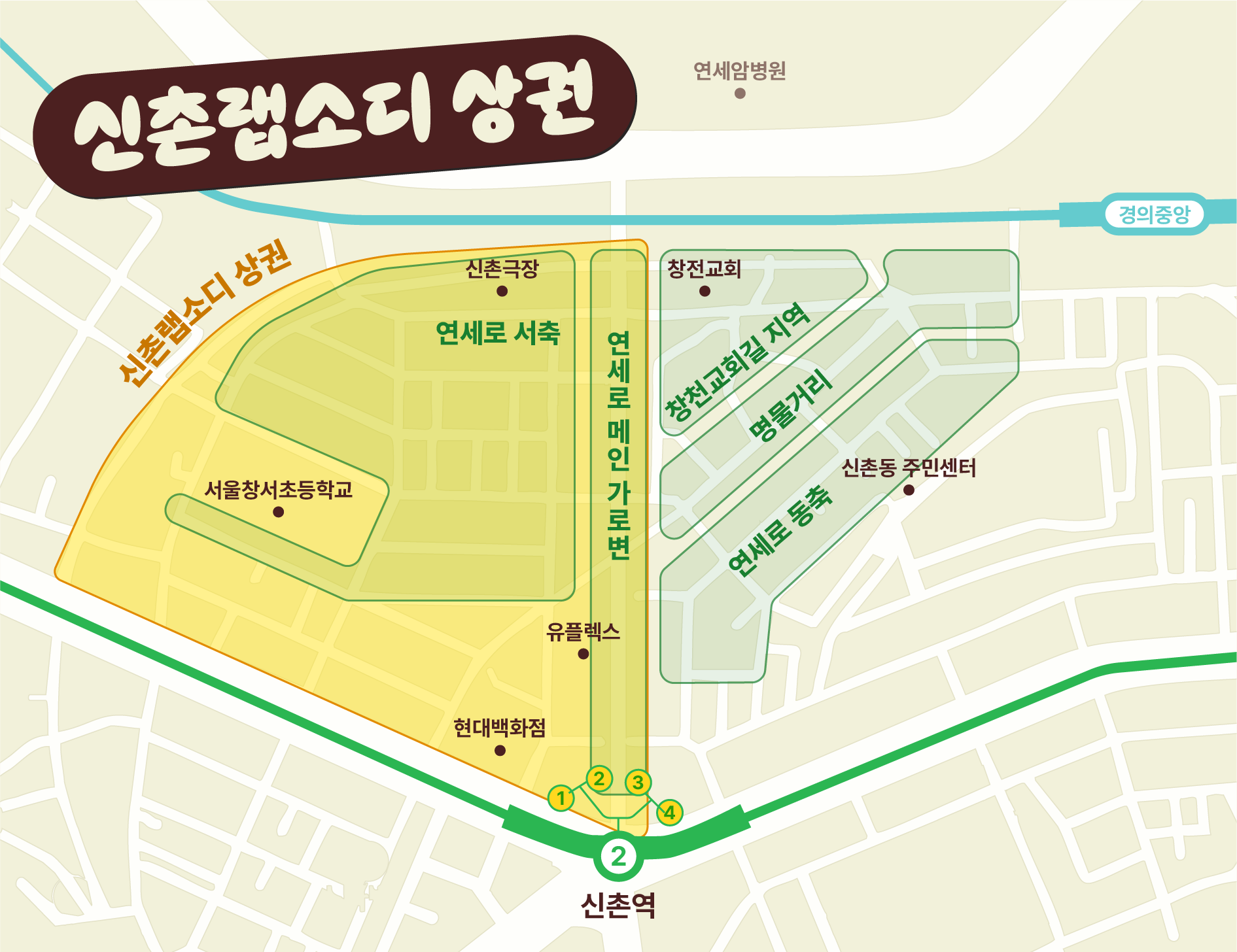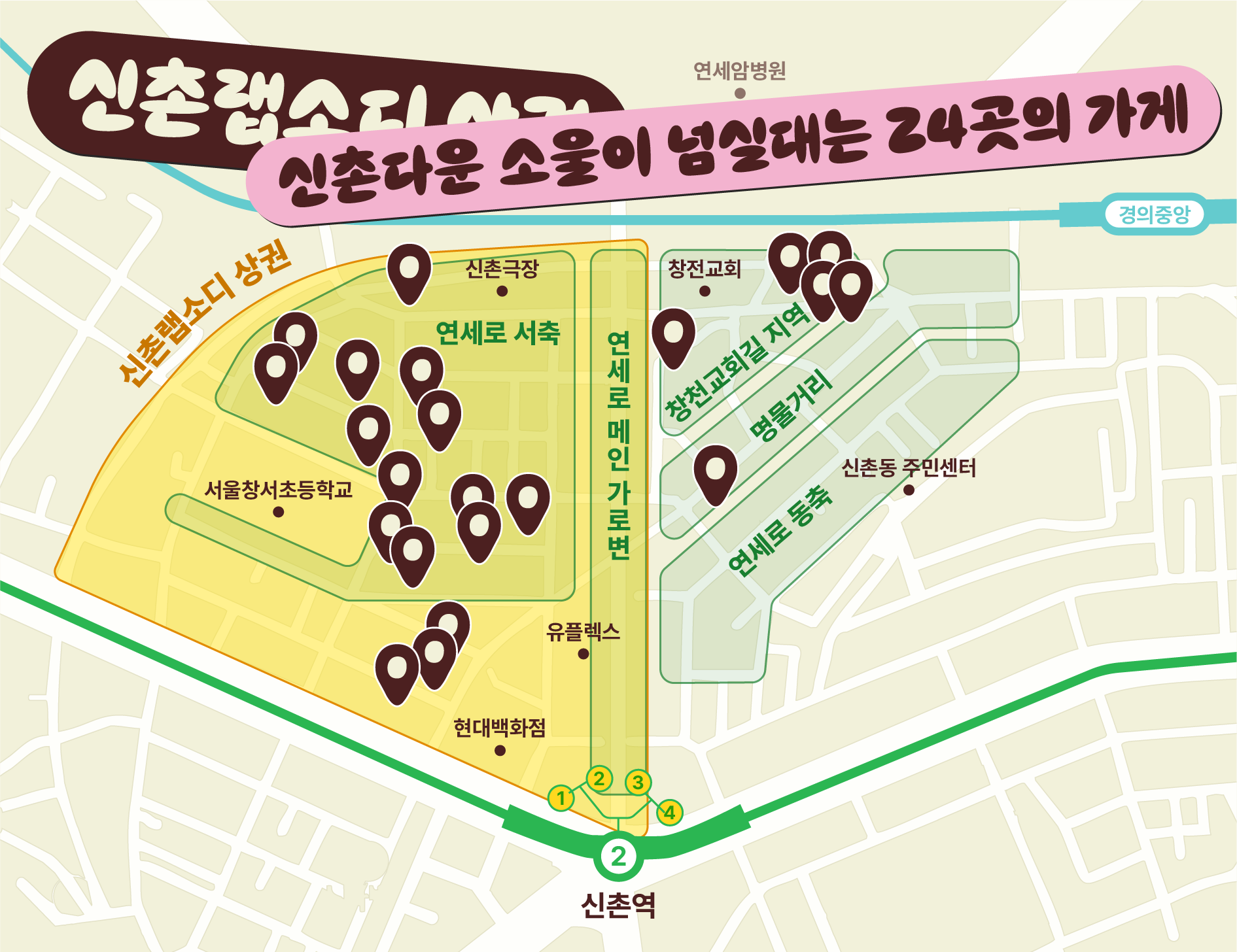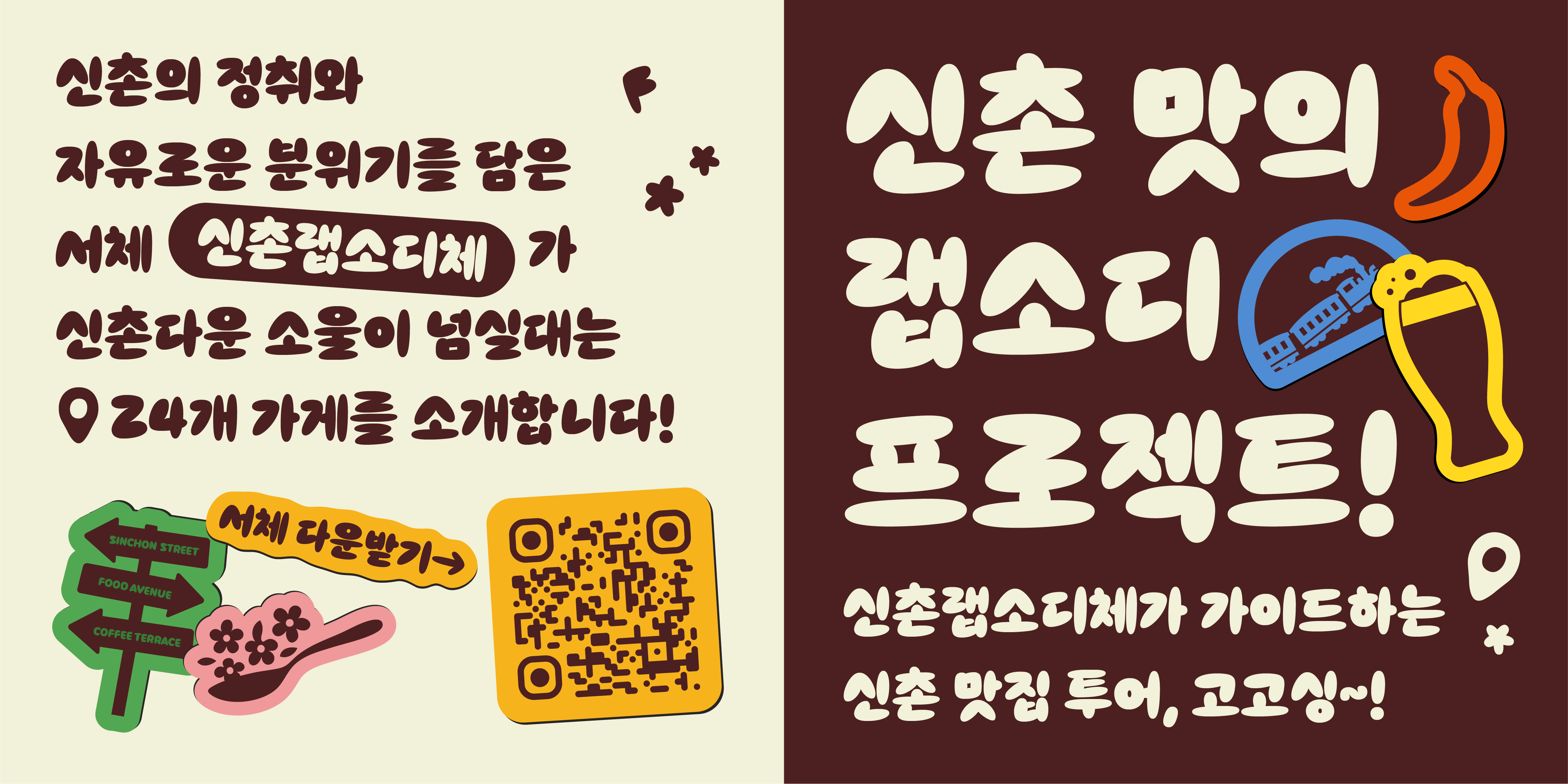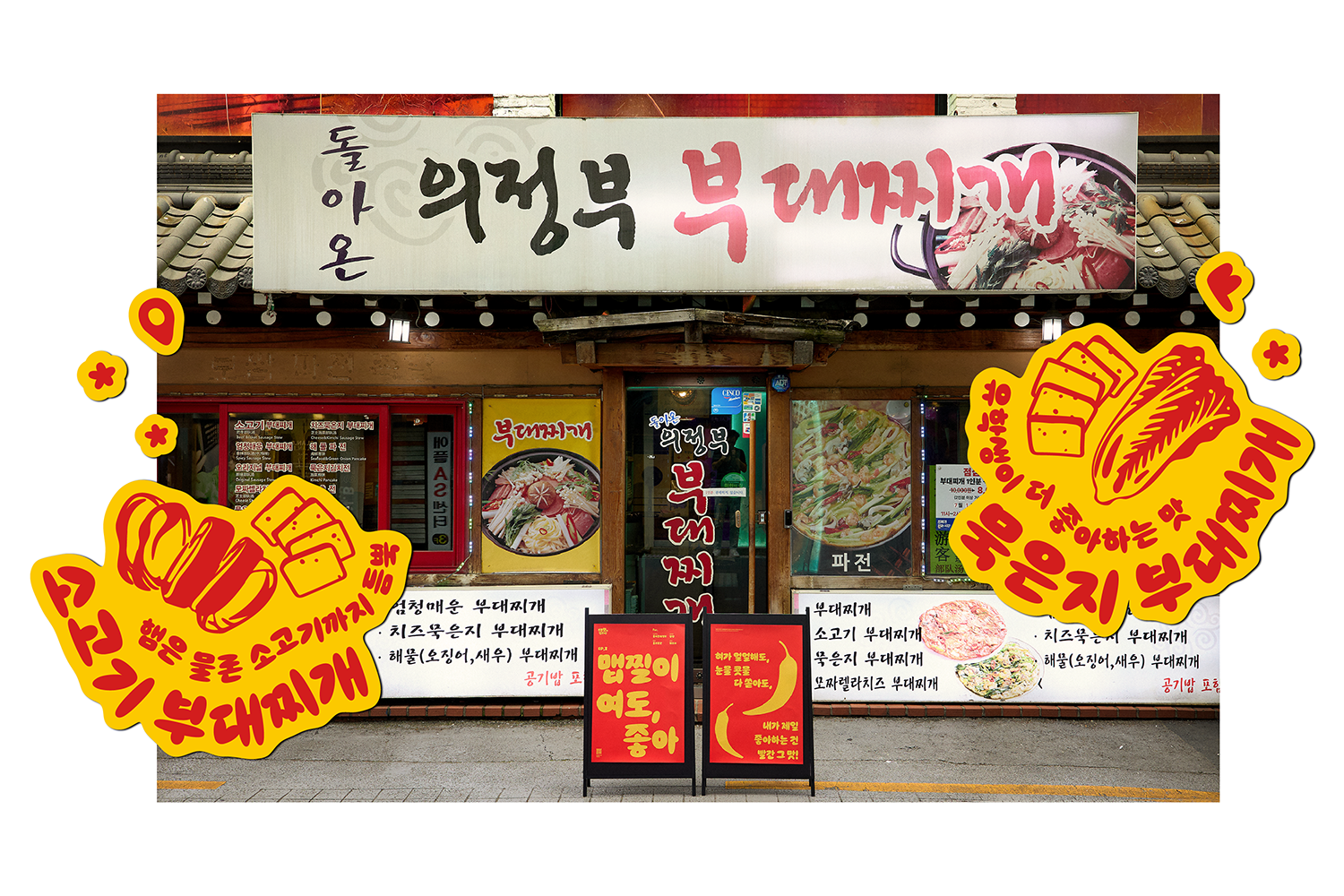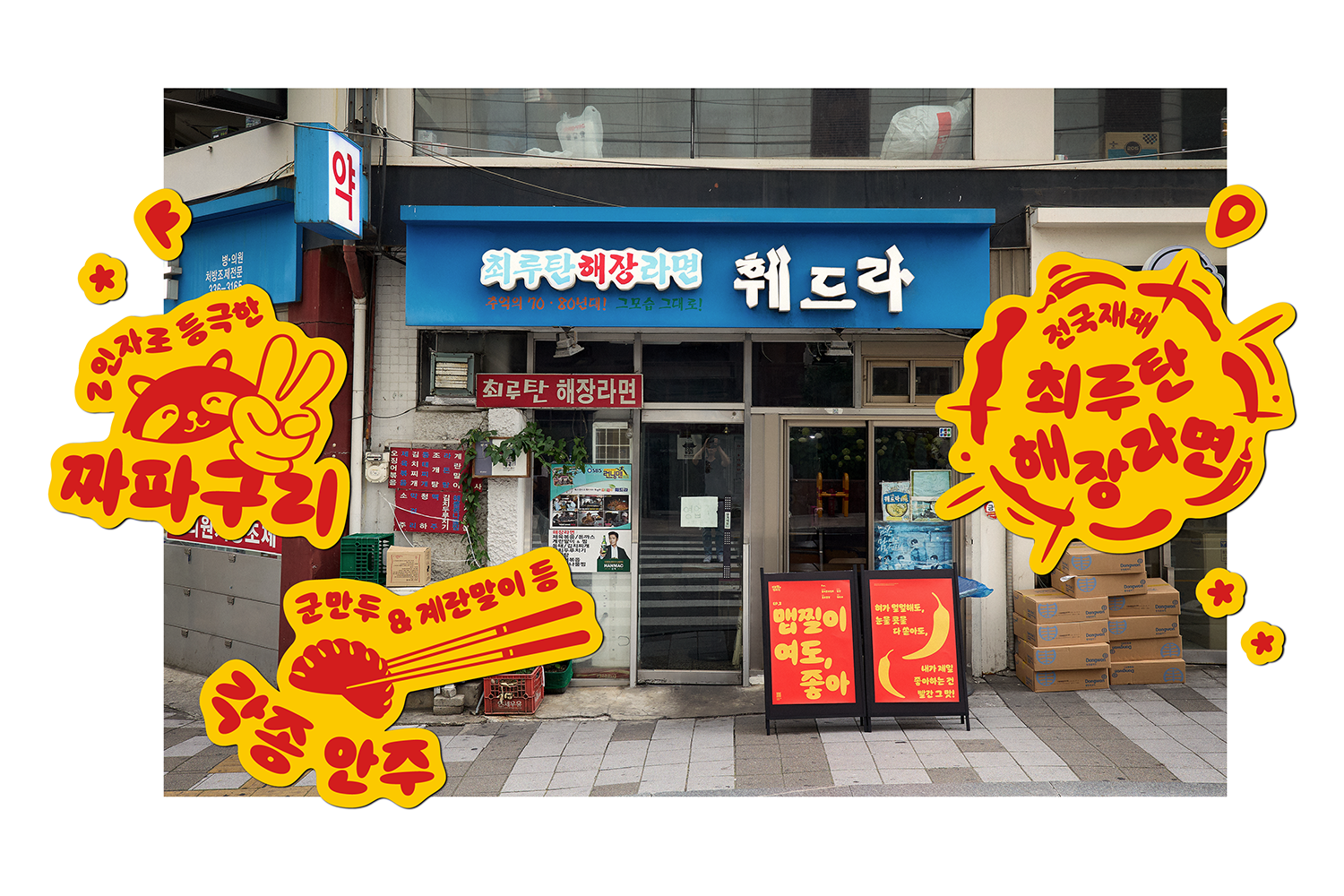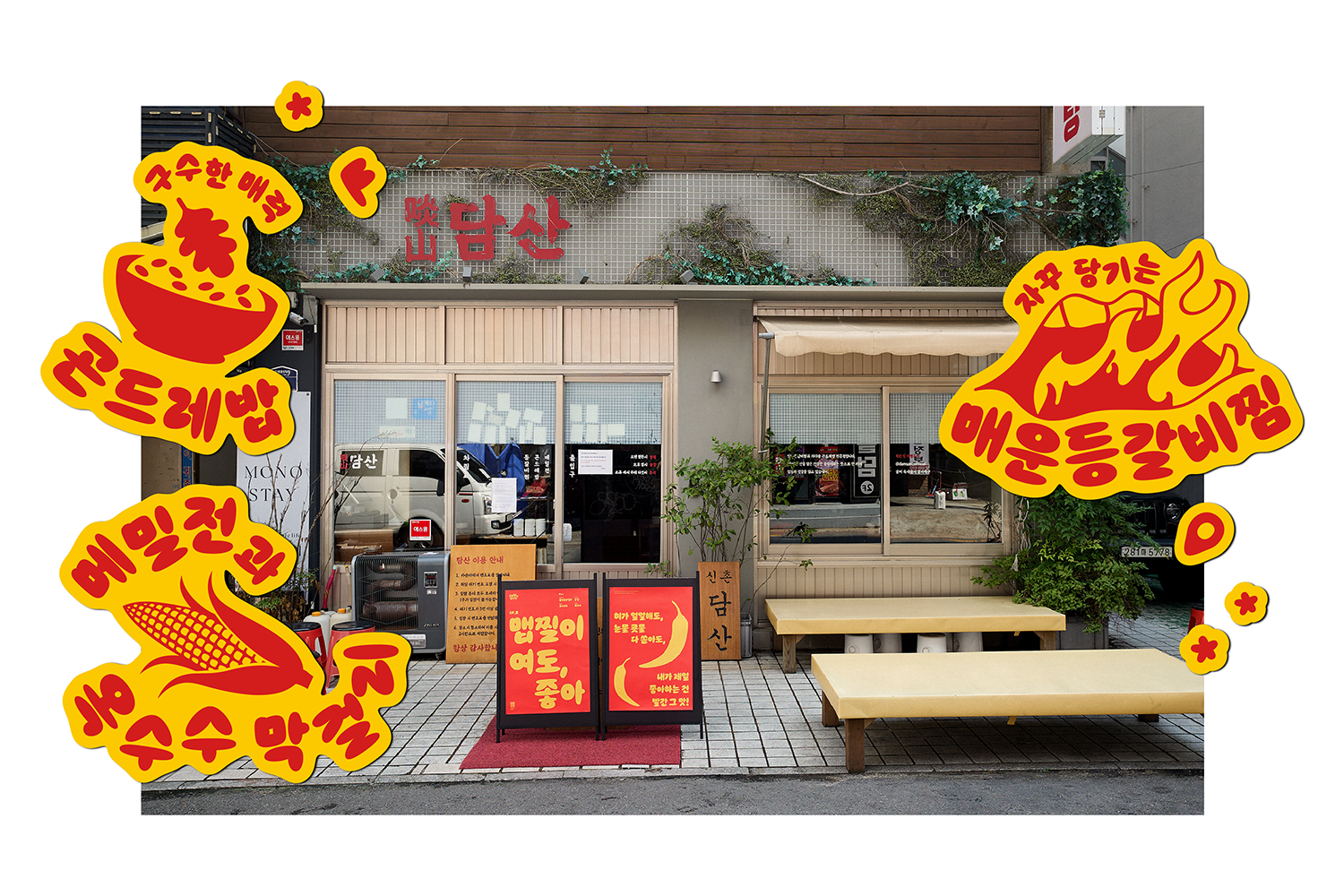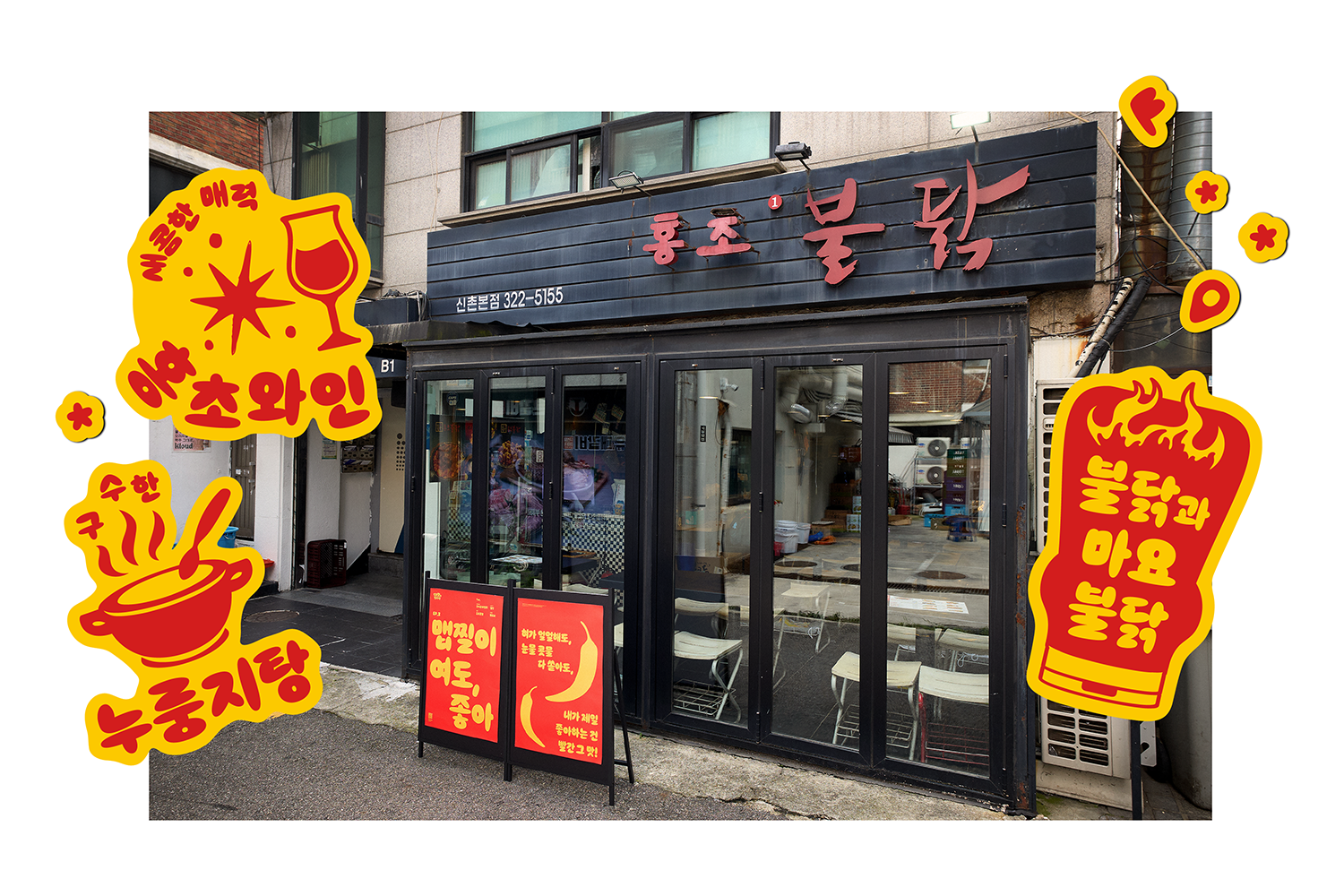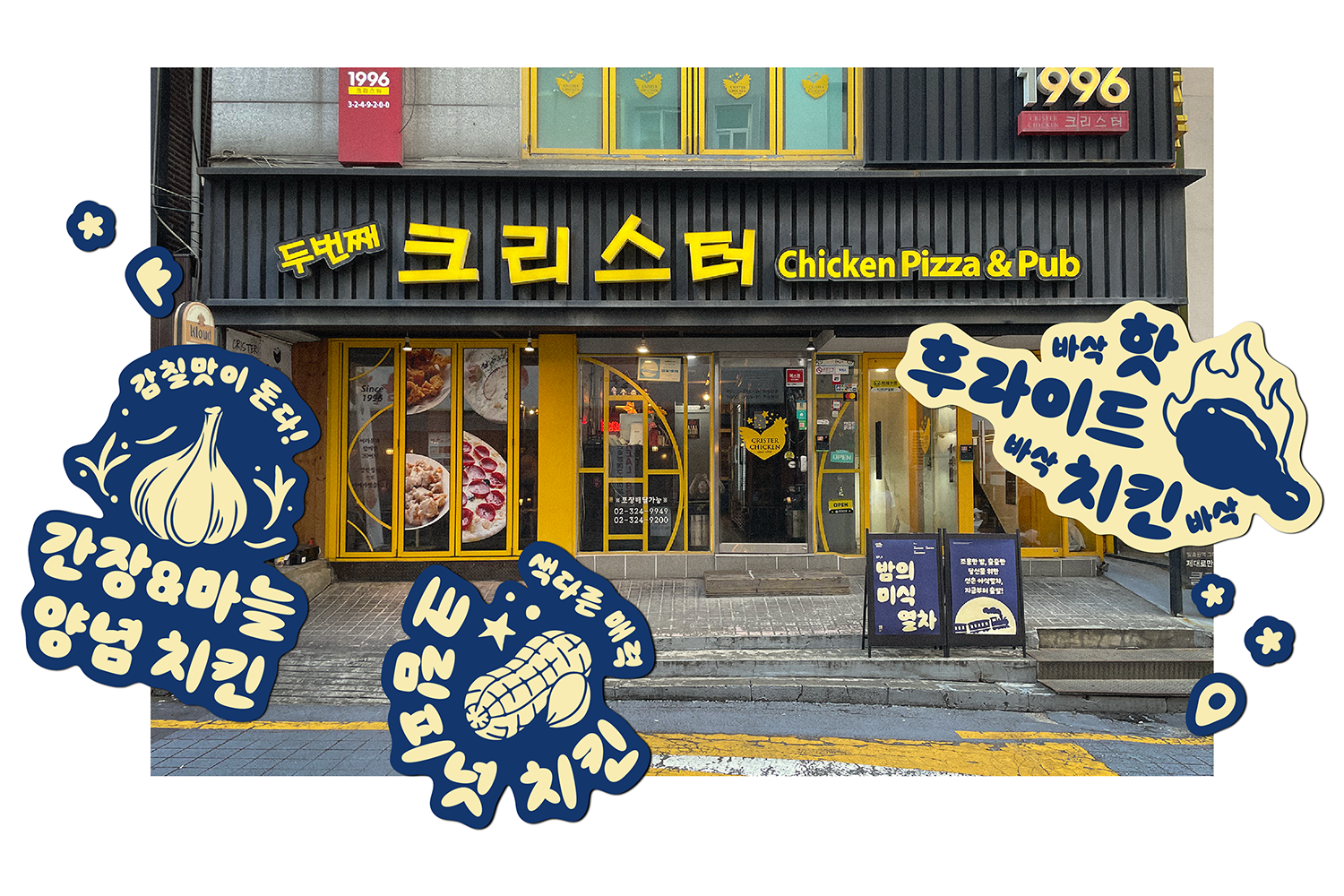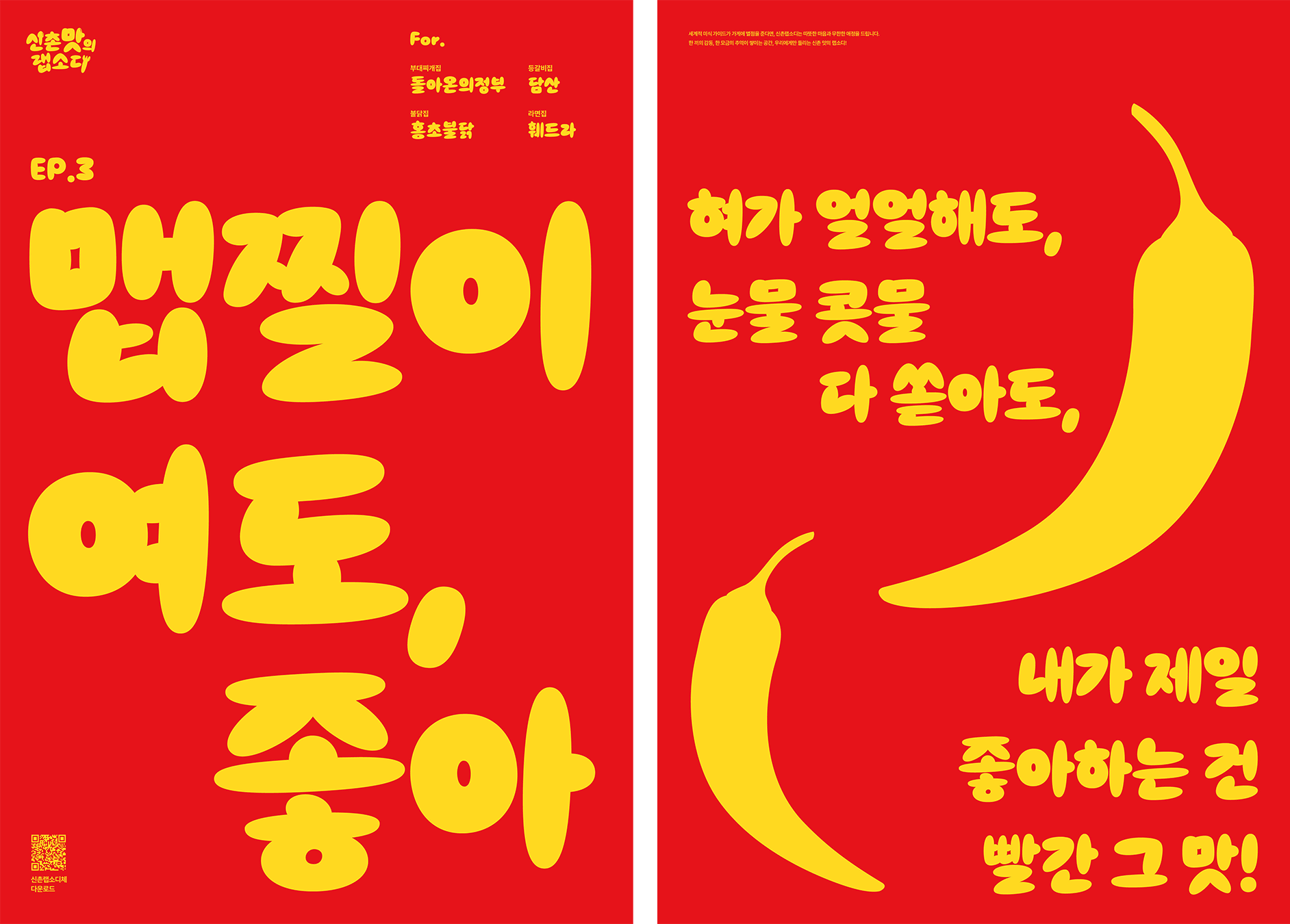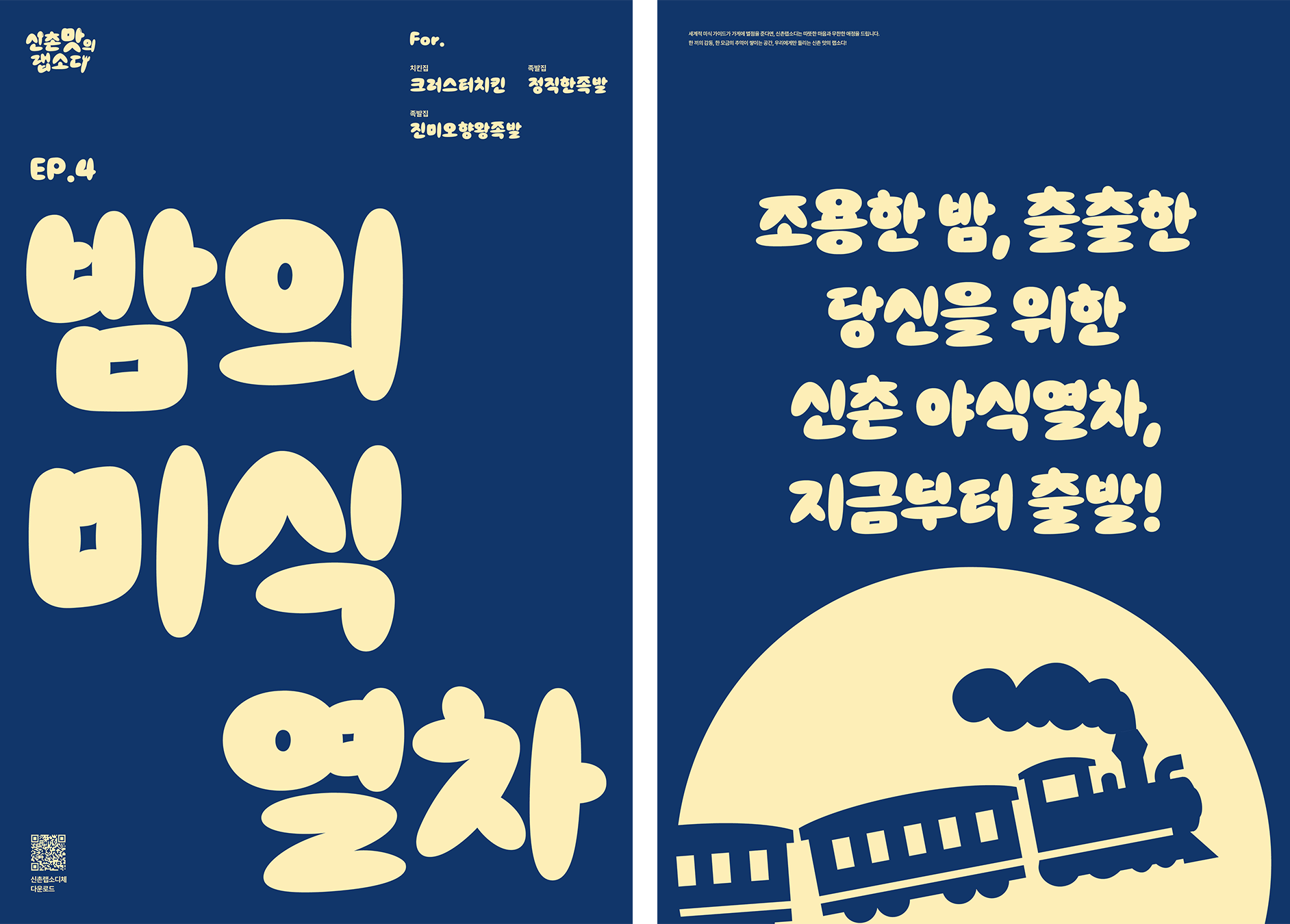
신촌랩소디체가 가이드하는 신촌 맛집 투어 시리즈 2
지금, 신촌의 여름은 무척이나 시원합니다. 이 무더위에 무슨 뚱딴지같은 말이냐고요? 땀이 쑥 빠질 만큼 매콤한 맛, 바삭바삭한 튀김 옷과 시원한 탄산감의 조화, 밤의 허기를 달래주는 쫄깃한 식감. 한 입이면 더위와 스트레스를 날려버리는 음식들이 하루 내내 여러분을 기다리고 있기 때문이죠. 폭염의 나날, 이열치열의 이치를 깨닫게 하는 매운맛과 야식의 유혹을 느끼러 신촌랩소디 상권으로 다시 떠나볼까요?
신촌랩소디체가 가이드하는 신촌 맛집 투어 시리즈 2
:  EP 3. 맵찔이여도 좋아 빨간 그 맛 & EP 4. 밤의 미식 열차, 출발 야식 특급
지금, 신촌의 여름은 무척이나 시원합니다. 이 무더위에 무슨 뚱딴지같은 말이냐고요? 땀이 쑥 빠질 만큼 매콤한 맛, 바삭바삭한 튀김 옷과 시원한 탄산감의 조화, 밤의 허기를 달래주는 쫄깃한 식감. 한 입이면 더위와 스트레스를 날려버리는 음식들이 하루 내내 여러분을 기다리고 있기 때문이죠. 폭염의 나날, 이열치열의 이치를 깨닫게 하는 매운맛과 야식의 유혹을 느끼러 신촌랩소디 상권으로 다시 떠나볼까요?
2탄에서는 입속의 방화범인 빨간 맛 그리고 밤을 책임지는 야식 명소들을 소개합니다. 이름만 들어도 군침이 도는 그 가게, 오늘의 주인공은 바로 여러분입니다.
• 복습하기 하나. 신촌랩소디 상권은?
연세로를 중심으로 펼쳐진 ‘신촌랩소디 상권’은 신촌의 오래된 골목과 개성 있는 가게들이 모인 곳입니다. 문화, 예술, 낭만, 젊음이 공존하는 이곳은 신촌만의 감성을 고스란히 전달합니다.
• 복습하기 둘. 신촌랩소디체는?
‘신촌랩소디체’는 신촌의 정취와 자유로운 분위기를 담은 서체입니다.
활기와 낭만이 공존하는 신촌의 거리처럼, 다채로운 리듬과 이야기를 글자에 담았습니다.
[EP 3. 맵찔이여도 좋아, 빨간 그 맛]
“혀가 얼얼해도 눈물 콧물 다 쏟아도, 내가 제일 좋아하는 건 빨간 그 맛!”
땀이 송골송골 맺혀도 멈출 수 없는 매운맛의 유혹, 한국인이라면 누구나 공감하는 ‘빨간 맛’의 힘! 매콤한 맛의 인기는 이 무더운 여름에도 좀처럼 식을 줄 모릅니다. 한 입 먹고 호들갑 떠는 맵찔이지만, 이열치열이라는 말로 합리화하며 매콤한 맛집들을 탐색하고 있다면, 속 시원한 부대찌개부터 불닭, 라면, 중독적인 갈비찜까지! 코스로 준비되어 있는 신촌랩소디 상권으로 떠나보는 거 어떨까요?
한국인에게 국물이 갖는 의미는 무엇일까요? 신촌랩소디 상권에는 답답한 가슴을 뻥 뚫어주는 국물 맛집이 두 군데나 있습니다. <돌아온 의정부 부대찌개>는 신촌 인근의 학생들은 물론 유학생에게도 사랑받는 ‘찐’ 부대찌개 맛집입니다. 고기와 햄이 아낌없이 들어간 소고기 부대찌개와 시원한 국물 맛을 자랑하는 묵은지 부대찌개가 인기 메뉴인데요. 소고기와 묵은지의 조합이라니 벌써부터 침이 꼴깍 넘어갑니다. 특유의 시원한 국물이 MSG 대신 진심과 정성을 푹 끓여낸 결과물이라는 사실 역시 놀랍기만 한데요. 끓일수록 깊어지는 국물 맛은 물론이고 정겨운 가게 분위기, 한결같은 사장님의 인자함까지. <돌아온 의정부 부대찌개>의 넘치는 매력들이 오늘도 기꺼이 부대찌개 한 그릇을 먹어야 할 이유가 되어줍니다.
다음으로 <훼드라>는 최루탄 해장라면으로 유명한 신촌의 대표 노포입니다. 최루탄 해장라면은 진한 육수를 베이스로 콩나물과 바지락까지 챙겨 넣은 칼칼한 라면인데요. 몇 해 전 편의점에서 기획 상품으로 출시될 만큼 유명한 메뉴랍니다. 단, 위장이 약하다면 속이 쓰릴 수 있으니 맵기 조절은 필수! 해장하고 가려다가 눌러앉아 한 잔 더 하게 만든다는 마성의 메뉴와 함께 올여름 이열치열을 실천해보세요!
🍲 돌아온 의정부 부대찌개 | 유학생이 더 좋아하는 ‘찐’ 부대찌개
🍜 훼드라 | 진정한 신촌러라면 최루탄 라면으로 해장
<담산>은 매운맛 이전에 분위기 맛집으로도 유명합니다. 깔끔한 인테리어로 특별한 기분을 내고 싶을 때 찾아오는 손님들이 많다고 하는데요. 그러나 일단 <담산>의 매운 등갈비찜 맛을 보고 나면, 이곳이 단순히 깔끔하고 트렌디한 가게가 아닌 깊이와 철학으로 승부하는 식당이라는 사실을 깨닫게 됩니다. 자극적이고 인위적인 매운맛 대신 깊이 있는 감칠맛으로 매운 걸 알면서도 자꾸 당기게 만드는 고급 스킬을 시전하거든요. 양념이 잘 밴 부드러운 등갈비찜에 혀가 얼얼해 갈 즈음, 곤드레밥, 메밀전, 옥수수 막걸리를 곁들이면 최고의 먹궁합 탄생입니다. 중독의 서막이라는 이 찰떡 조합, 올여름이 가기 전에 꼭 맛본다면 좋겠죠?
다음으로 살펴볼 메뉴는 무려 불닭입니다. 사람들이 치맥을 즐길 때, 신촌에서는 불홍 조합을 맛볼 수 있다는 사실, 알고 계셨나요? 불맛 가득 머금은 불닭에 한 잔 곁들이고 싶다면 <홍초불닭>에서는 맥주 대신 홍초 와인을 추천합니다. 홍초에 소주를 섞어 직접 제조하면 되는데, 매콤한 불닭과 궁합이 아주 훌륭하답니다. 매운 걸 잘 못 먹는 맵찔이라면 사이드 메뉴를 적극 활용해보세요. 클래식한 주먹밥과 계란찜은 물론 어묵탕, 누룽지탕까지. 불닭 더 맛있게 먹는 법 연구하러 온 단골들로 오늘도 <홍초불닭>이 북적입니다.
🐖 담산 | 감칠맛에 자꾸 당기는 명품 매운갈비
🌶 홍초불닭 | 불닭과 홍초와인의 맛있는 유혹
[EP 4. 밤의 미식 열차, 출발 야식 특급]
“조용한 밤, 출출한 당신을 위한 신촌 야식 열차, 지금부터 출발!”
“어른들을 위한 야식 열차, 신촌역 도착이오!” 신촌의 밤을 낮보다 더 즐겁게 만드는 요소, 뭐니 뭐니 해도 든든한 야식입니다. 무더운 하루를 마치고 허기와 피곤함이 몰려오는 밤, 든든한 야식으로 완벽한 마침표를 찍어 볼까요? 야식의 대명사인 치킨 그리고 족발 딱 두 가지 메뉴만 제대로 소개하겠습니다. 배달도 좋지만 직접 가서 먹어야 더 맛있다는 세 곳의 가게로 떠나보시죠!
1996년부터 신촌의 치킨 계를 평정하고 있는 이곳, 이름부터 바삭한 <크리스터치킨>입니다. 국내산 냉장 닭을 깨끗한 기름에 튀겨 수많은 브랜드 치킨의 시대에 수제 치킨의 품격을 보여주지요. 근본은 바삭한 핫 후라이드 그리고 양념치킨이지만 간장, 마늘, 크림피넛 등 맛있는 시도를 이어가고 있습니다. 치킨 이야기를 하는데 맥주가 빠지면 섭섭하죠. 기본 생맥주, 병맥주는 물론 페어링하는 재미가 있는 수제 맥주들까지 다양하게 구비해 신촌의 치킨 성지 역할을 톡톡히 이어가고 있습니다. 느끼함이 몰려올 땐, 골뱅이 소면을 슬쩍 추가해보세요!
🍗 크러스터치킨 | 바삭함을 넘어선 신촌 스타일 치킨
가게 이름에 ‘정직’을 쓸 수 있는 곳, 세상에 몇 군데나 될까요? <정직한족발>에서는 이름을 꼭 닮은 정직한 퀄리티의 족발과 보쌈을 만나볼 수 있습니다. 족발 한 점 한 점, 잡내 없는 부드러운 살코기와 쫄깃한 껍질의 조화가 예술이지요. 기본에 충실한 일반 족발과 보쌈으로도 충분하지만, 매콤한 불족발과 참숯에 구워 불향을 입힌 숯불 불무뼈닭발을 곁들이면 그야말로 최고의 야식입니다. 메인 메뉴를 주문하면 막국수, 순댓국, 어묵탕 중 하나를 사이드로 선택할 수 있는데요. 대체로 막국수를 선택하지만 따뜻한 두 메뉴와의 조화도 훌륭하답니다.
신촌랩소디 상권을 지키는 또 하나의 족발 명소 <진미오향왕족발>입니다. 사실 이곳은 술꾼들을 위한 족발집인데요. 기본 메뉴로 순대가 세팅되고 족발에 막국수 대신 술국이 세트로 제공됩니다. 쫄깃한 족발로 입맛을 돋우고 따끈한 술국으로 속을 덥히며 한 잔 두 잔 잔 기울이다 보면, 신촌의 푸른 밤, 맛깔나게 익어갑니다.
🐷 정직한족발 | 믿음직한 족발 한 상
🐷 진미오향왕족발 | 족발과 술국의 색다른 하모니